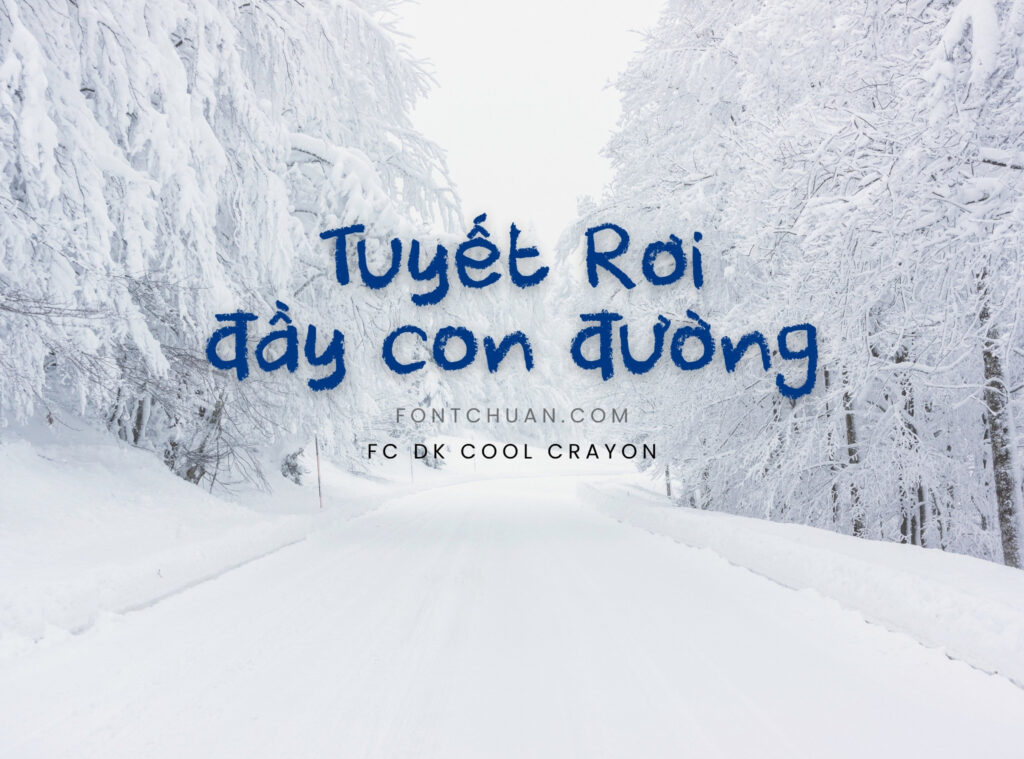
Font FC DK Cool Crayon Việt Hóa
Tác giả Font: David Kerkhoff
DK Cool Crayon là một font chữ viết tay nét phấn bảng gần giống như thư pháp rất độc đáo, được thiết kế bởi David Kerkhoff. Font này mang phong cách vẽ phấn, tạo cảm giác thân thiện và gần gũi, phù hợp cho các dự án thiết kế như thiệp mời, tiêu đề, poster và các ấn phẩm dành cho trẻ em. Với các đường nét mềm mại và tự nhiên, DK Cool Crayon mang lại sự ấm áp và thu hút cho người xem. Ngoài ra, font này cũng có thể được sử dụng như một Font chữ Giáng Sinh cho các thiệp, poster, banner mùa lễ hội, hoặc làm font ngày nhà giáo Việt Nam để trang trí các thiệp, poster chúc mừng thầy cô, mang lại không khí ấm cúng và vui tươi.
Về đặc điểm thiết kế, FC DK Cool Crayon sở hữu các ký tự được thiết kế tỉ mỉ, cấu trúc chữ cân đối và hỗ trợ đa ngôn ngữ, lý tưởng cho nhiều mục đích sử dụng trong như giảng dạy, các ấn phẩm ngành giáo dục, và các thiết kế tiêu đề, bao bì sản phẩm và các ấn phẩm truyền thông khác.
Ngoài ra, FC DK Cool Crayon cũng là lựa chọn thú vị khi kết hợp với font chữ Tết trong các thiết kế mùa xuân. Trong khi DK Cool Crayon mang lại nét phấn bảng gần gũi, thì font chữ Tết đem đến sự rực rỡ, tươi mới. Sự kết hợp này giúp các sản phẩm như poster, thiệp chúc mừng hay banner Tết trở nên vừa thân thiện, vừa tràn đầy không khí lễ hội.